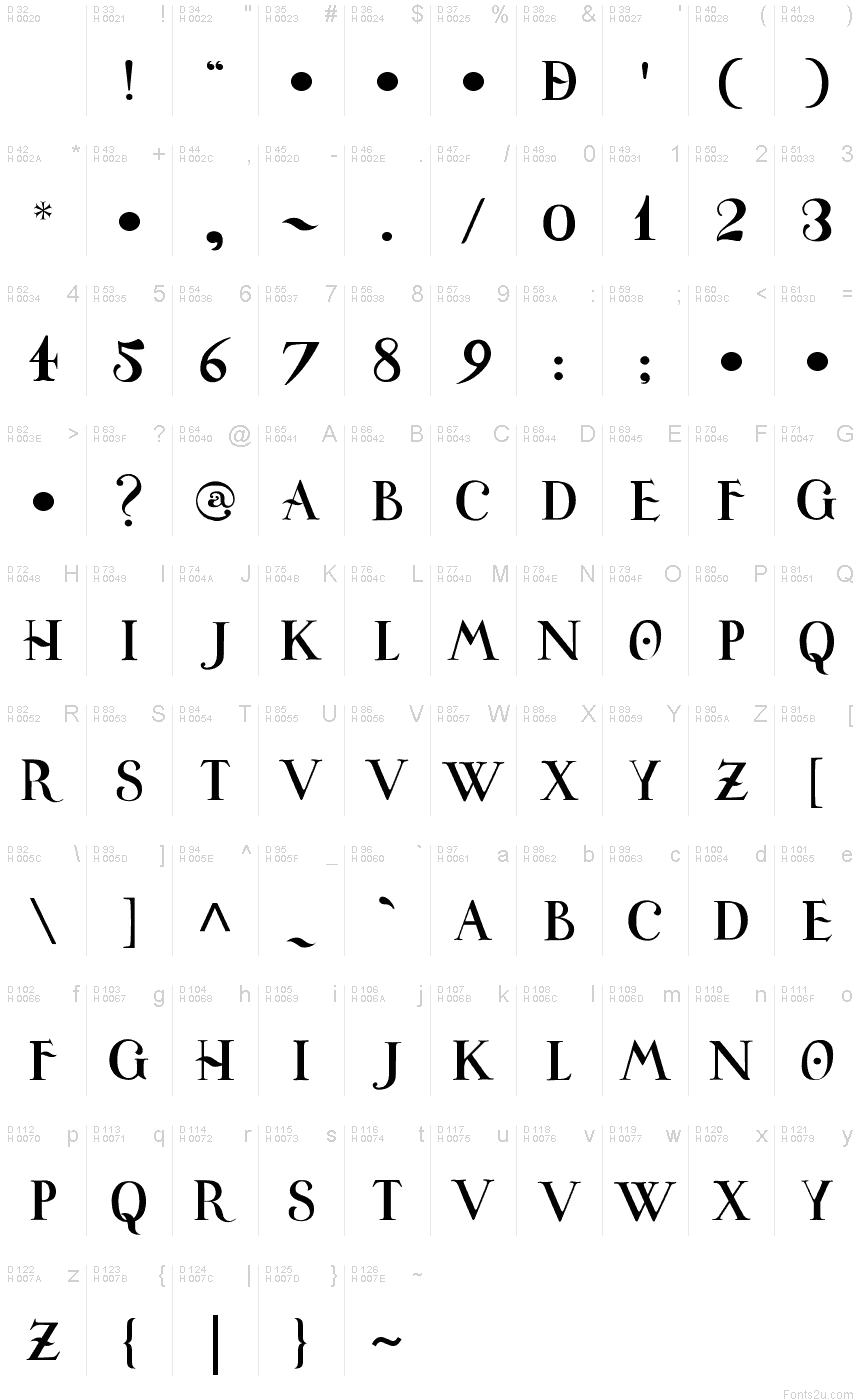
معاينة خط Universitas Studii Salamantini
Universitas Studii Salamantini هو خط مجاني من USAL مستوحى من النقوش الرومانية الكلاسيكية، ويتميز بحروف كبيرة مرتفعة، وضربات حادة تشبه الإسفين، وإيقاع هادئ وضخم. تبدو الحروف احتفالية وليست مزخرفة، مع خطوط رفيعة دقيقة وتباين حاد وتفاصيل ممتدة بنعومة تمنح الخط طابعاً أكاديمياً وتاريخياً.
يتناسب الخط بشكل طبيعي مع الهوية البصرية للجامعات، وملصقات المتاحف، وأغلفة الكتب، وعناوين المعارض، وبرامج الفعاليات التي تتطلب طابعاً رسمياً عريقاً يحدد الأجواء. كونه خطاً مجانياً، فهو مناسب أيضاً لبطاقات العناوين وبدايات الفصول والشعارات، خاصة عندما تريد أن تبدو الحروف الكبيرة منحوتة ووقورة دون تكلف.
يُستخدم هذا الخط من قبل خريجي جامعة سالامانكا منذ القرن الخامس عشر. كان الطلاب يكتبون أو يرسمون على جدران الجامعة بدم الثيران.
تم تكليف الجامعة بتصميم هذا الخط في القرن العشرين لمنحها هويتها الخاصة.
حتى سنوات قليلة مضت، كان خط Universitas Studii Salamantini مخصصاً للاستخدام الحصري من قبل المعلمين والطلاب.
استخدم علامة & للحصول على الرابطة القديمة المكونة من حرفي D و E.